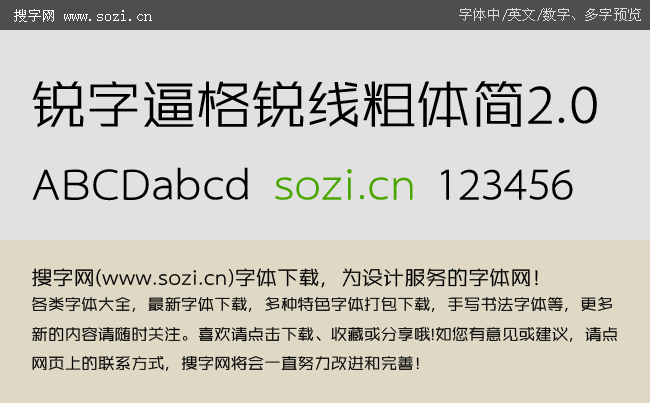
銳字逼格銳線粗體簡2.0
搜字網(wǎng)提供一款銳字逼格銳線粗體簡中文字體下載,銳字逼格銳線粗體簡是一款應(yīng)用于設(shè)計方面的中文簡體漢字,該字體端正大方,擁有卡通風格,整體效果非常出眾,并且字庫完整,可以應(yīng)用于廣告設(shè)計、名片設(shè)計、包裝印刷、產(chǎn)品設(shè)計等應(yīng)用。